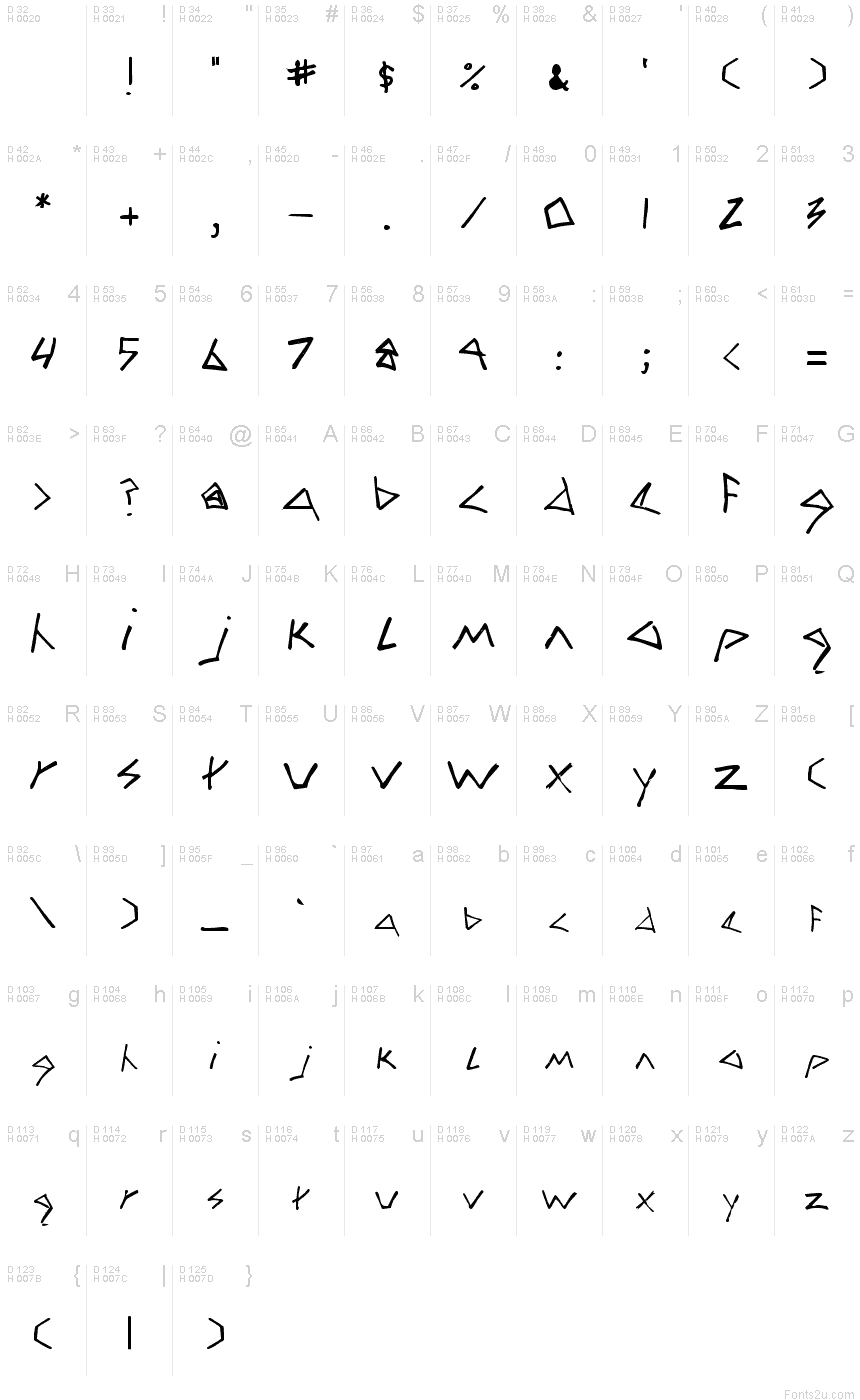
خط Zag من تصميم أندي كرالينغ هو خط يدوي مجاني يتميز بلمسة حادة وعفوية أشبه بالاسكتش. تبدو الحروف وكأنها خُطّت بسرعة بقلم التحديد، فهي مليئة بالزوايا المائلة والأشكال المثلثة المفتوحة والضربات الطويلة التي تمتد تماماً بالقدر الذي يجعل إيقاع الخط مضطرباً وذا طابع خام.
هذا ما يجعل Zag خياراً طبيعياً لمجلات الزين، وعناوين الملصقات، وأغلفة الكاسيت، وبطاقات العناوين، ومسودات الشعارات حيث قد يبدو الخط المنمق أكثر من اللازم. كخط مجاني، يتألق Zag في النصوص القصيرة، خاصة في الشعارات أو العناوين الجذابة، حيث تضفي حركته المتقطعة والعفوية طابعاً فريداً على الكلمة بأكملها.